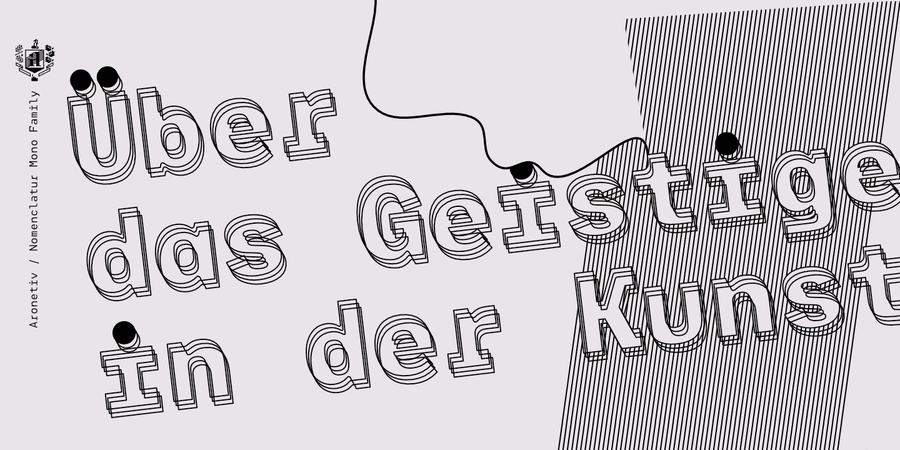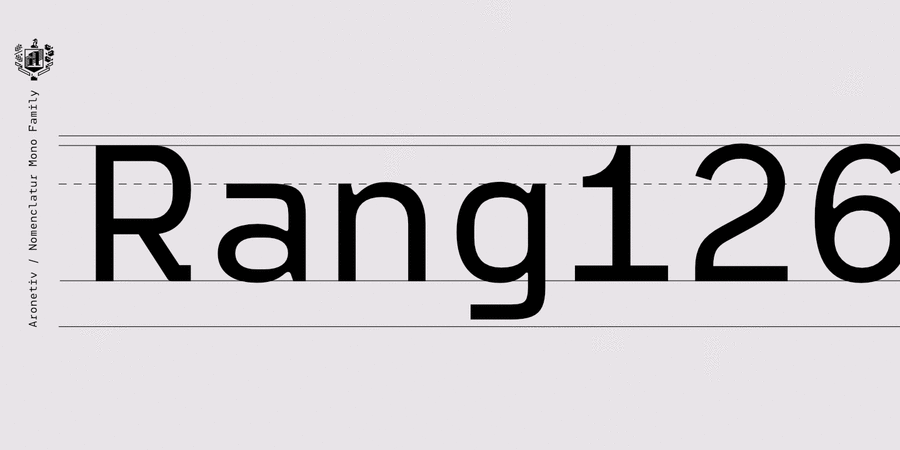
Моноширинне шрифтове сімейство Nomenclatur Mono створене спеціально для коду. Його унікальні елементи дизайну додають нотку креативності, зберігаючи професійне середовище кодування. Графіка літер досягає балансу між сучасною естетикою та функціональною чіткістю, поєднуючи загальний технічний вигляд із відтінком візуальної привабливості. Тому цей шрифт сподобається не тільки програмістав, але і дизайнерам. Гарнітура містить 15 накреслень + 1 варіативний шрифт. Широкий діапазон стилів від жирного до легкого і вузького задовольняє різноманітні вподобання, а постійна ширина символів забезпечує точне вирівнювання тексту. Цей шрифт підходить до типографічних експериментів. Авангардні дизайнерські нюанси в різних стилях додають емоцій. Шрифт розробив Олексій Поповцев у 2024 році.
Особливості сімейства шрифтів Nomenclatur MonoХіт десятиліття:
Асоціації з сімейством шрифтів Nomenclatur MonoОсобистість і характер гарнітури:
точний, рівний, прямокутний, стабільний, стійкий, техногенний, статичний, міський, глобалізований, глобалістічний, урбаністичний, розумний, худий, твердий, надійний, індустріальний, автоматичний, сталевий, міцний, сучасний, логічний, прагматичний, практичний, штучний, машинний, інженерний, креслярський, футуристичний, космічний, технічний, якісний, елементарний, доступний, залізний, стандартний, різкий, чіткий, комп'ютерний, зрозумілий, космополітичний, прямий, стиснений, стрункий, високий, переконливий, серйозний, впевнений, сильний, авторитетний, формальний, діловий, монотонний, залізничний, відповідальний, архітектурний, робочий, гучний, важкий, грубий, суворий, гострий, важливий, щільний, брутальний, армійський
техніка, прилад, архітектура, наука, дизайн, Місто, верстат, інструмент, урбаністика, гаджет, девайс, навігація, айтішник, IT, айті, технології, завод, інженер, автоматика, інститут, космос, промисловість, ракета, супутник, конструктор, креслення, рентген, хакер, фантастика, гра, електроніка, код, ГОСТ, комп'ютер, програмування, залізо, коворкінг, робот, комп'ютерна гра, астрономія, електростанція, енергетика, хмарочос, армія, машинобудування, порт, будівництво, вагон, залізниця, кінотеатр, ремонт, авіація, архітектор, робочий, шутер, авто, сталевар, нафта, паливо, кіно, мотор, двигун, літак, тара Гарнітура має ознаки стилів: